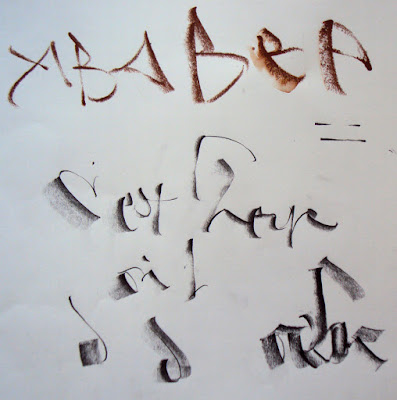
Laurent est gaucher... Pendant qu'il étudiait la calligraphie avec Kitty Sabatier, il a eu l'idée de travailler l'écriture du moment (cursive romaine) avec un critérium...
C'est ainsi qu'il a trouvé comment contourner les obstacles de l'encre et de sa lenteur de séchage, le point noir des gauchers !
Il nous a invité à faire quelques exercices d'échauffement > appui - relâche - appui ou l'inverse avec un critérium :
1 > des bâtons
2 > des lettres, puis l'alphabet, en majuscules, minuscules...
3 > une phrase
Puis nous avons testé différents crayons : crayon de papier plus ou moins gras, mine de plomb, pierre noire...
Puis les crayons de couleur, craies grasse, craie à la cire, crayon aquarellable...
Voici quelques unes des productions des stagiaires :
Voici ce que Laurent a réalisé à ma table... (exemple, test, etc.).